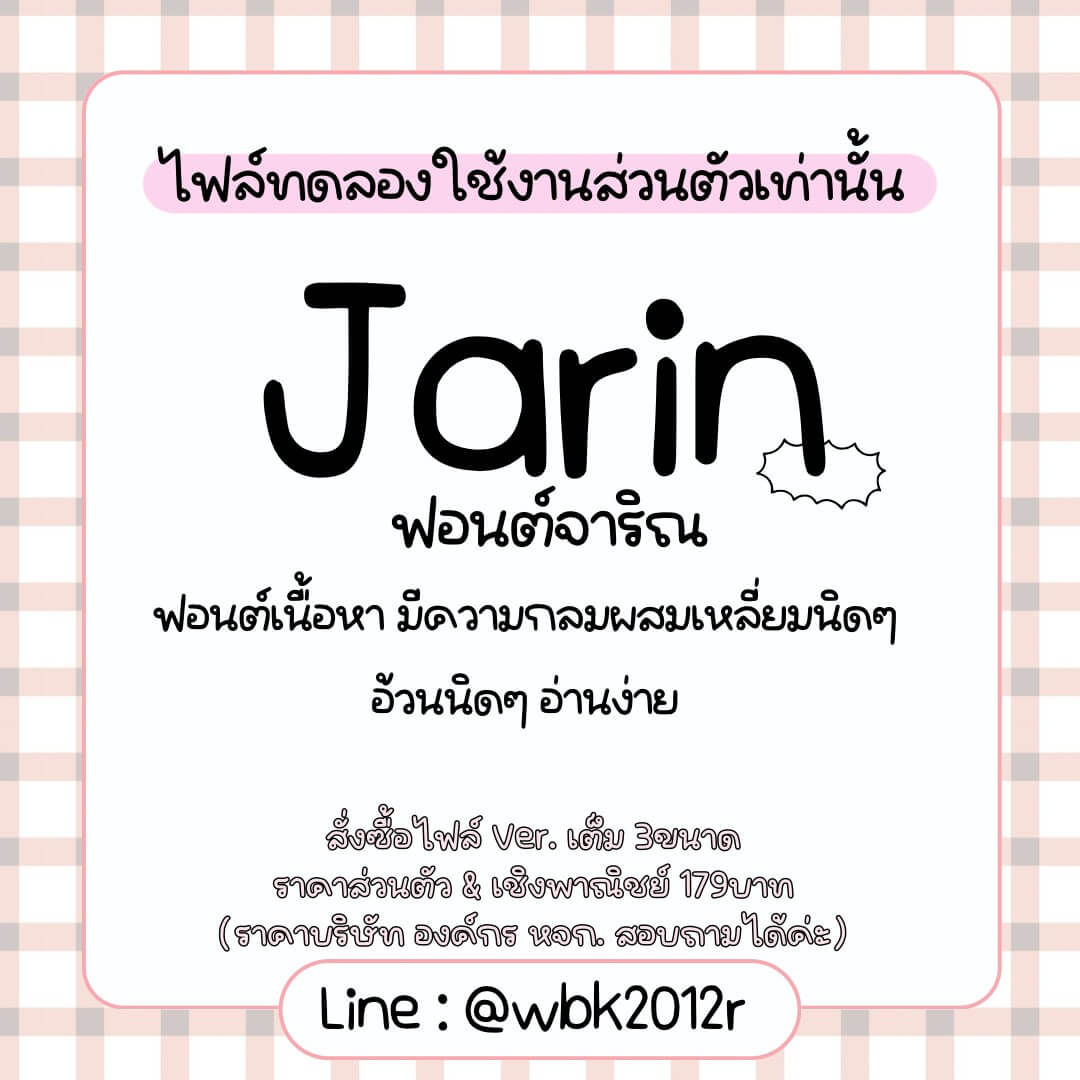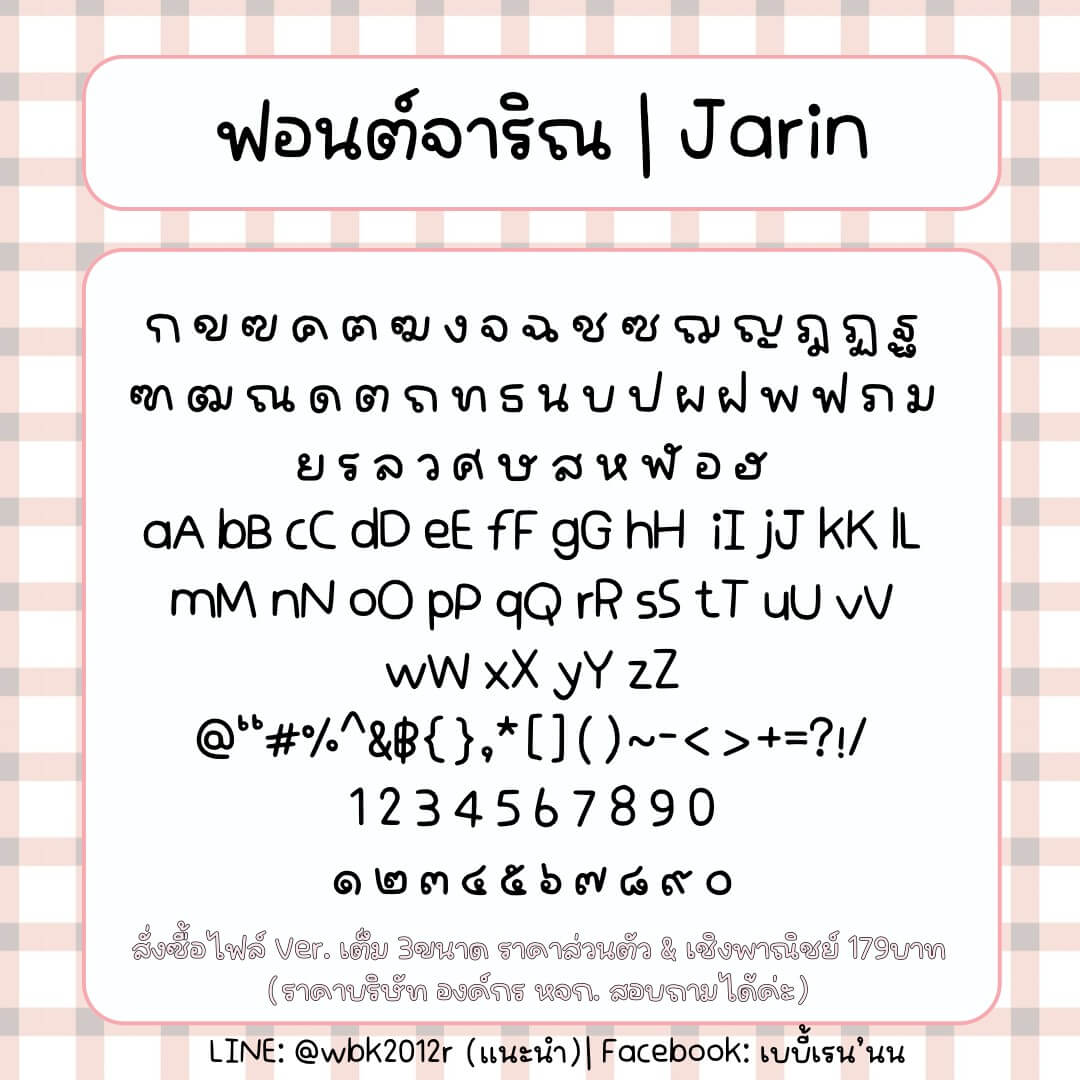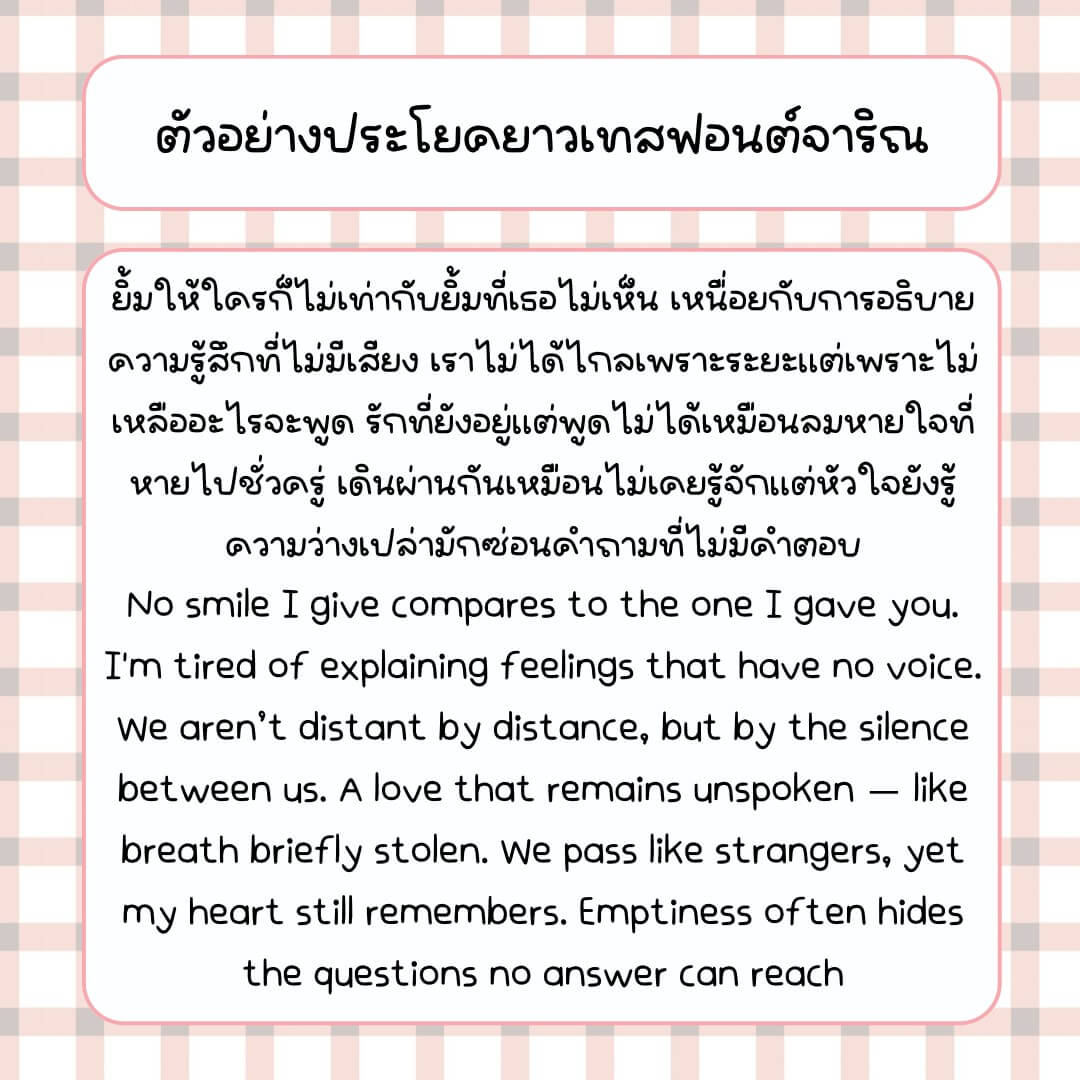
PRHJarin | จาริณฟอนต์ – ฟอนต์เนื้อหา มีความกลมผสมเหลี่ยมนิดๆ อ้วนนิดๆ อ่านง่ายค่ะ
- ฟอนต์มีขนาดไม่เท่ากัน / ไม่มีเลข/วรรณยุกต์ / อักษรโปร่งบางตัว
จาริณ (PRHJarin)